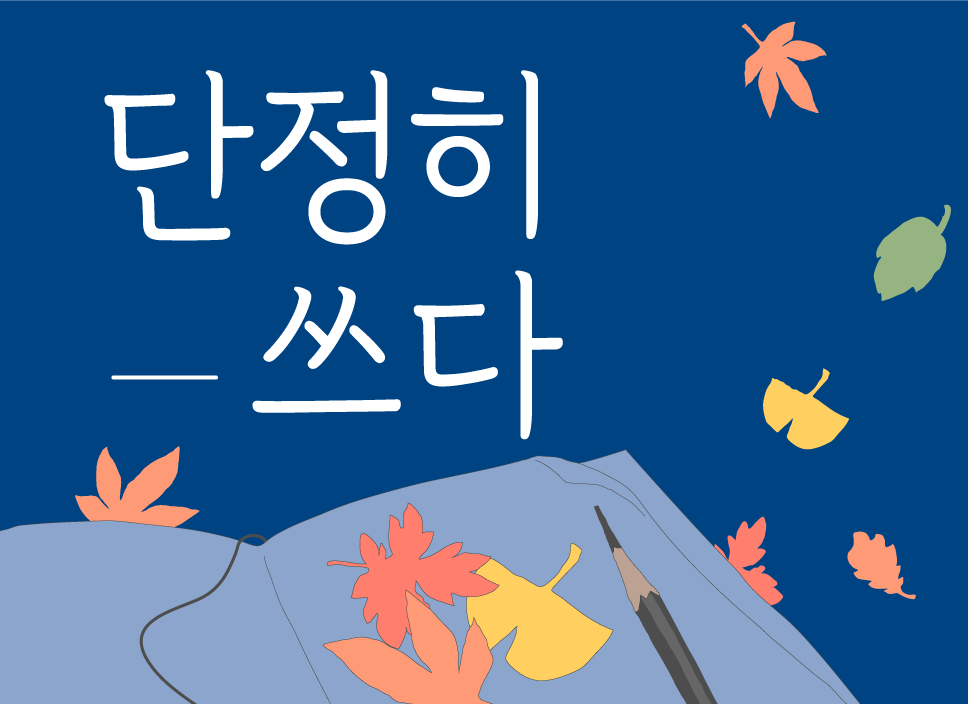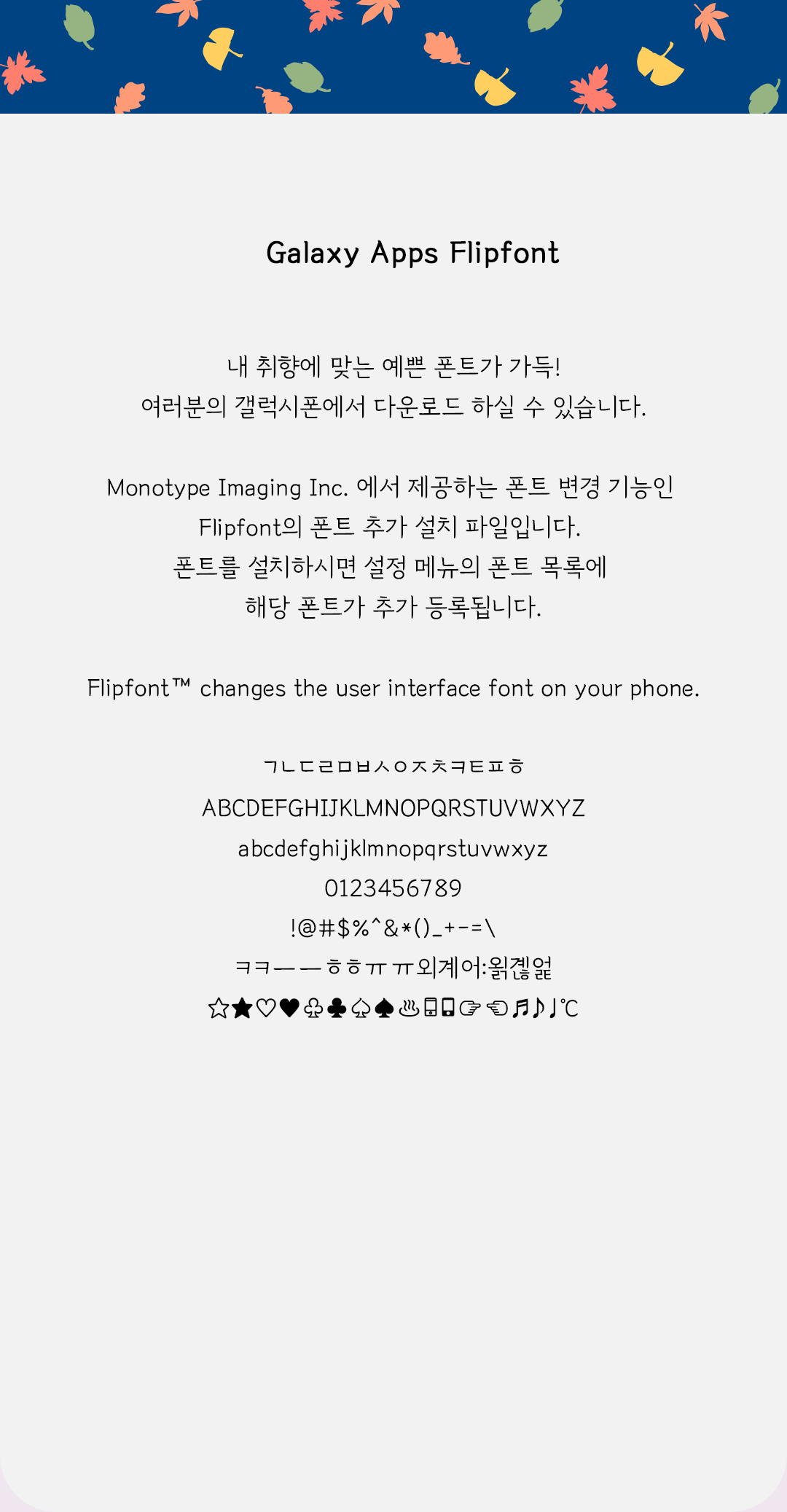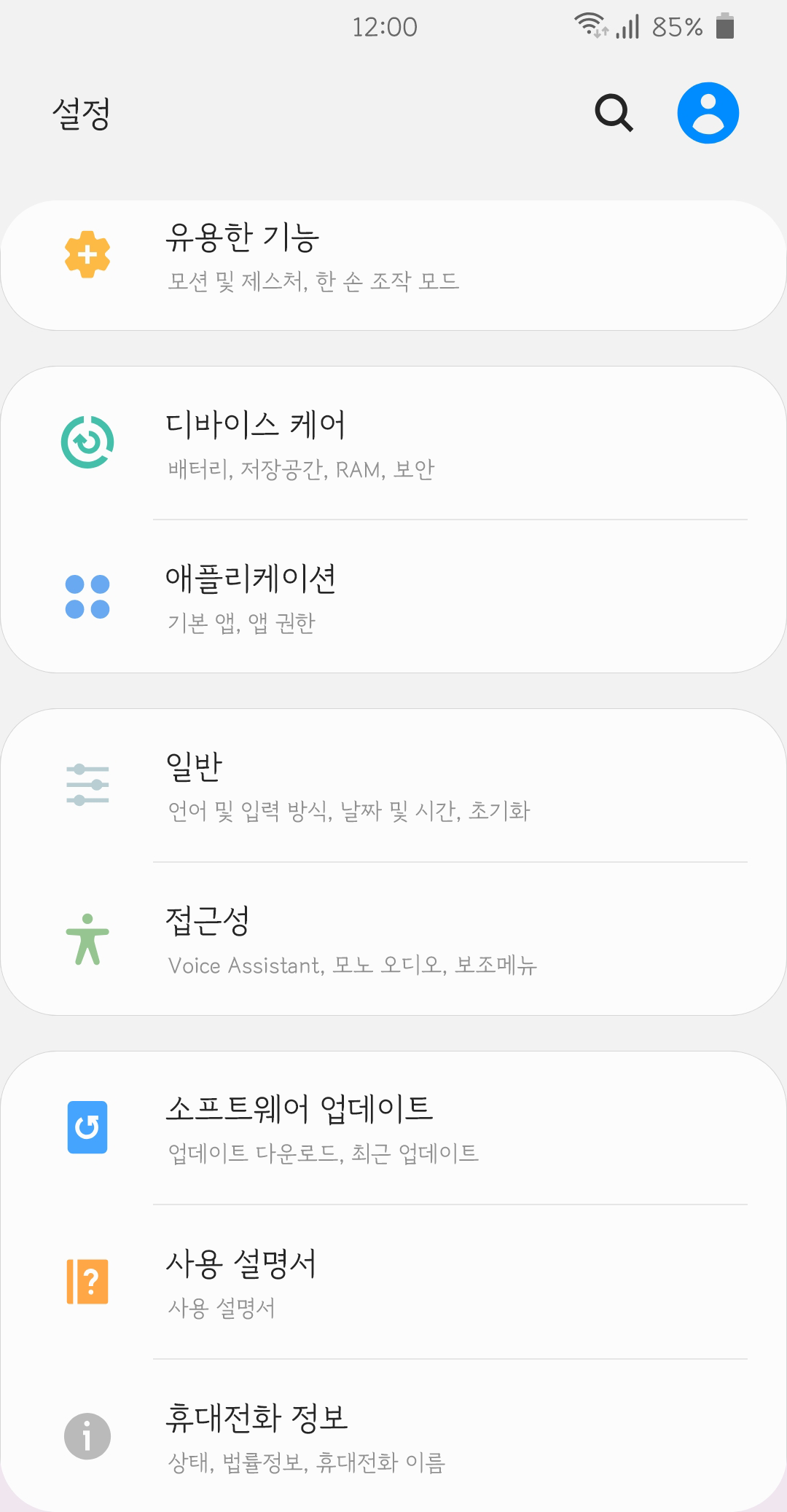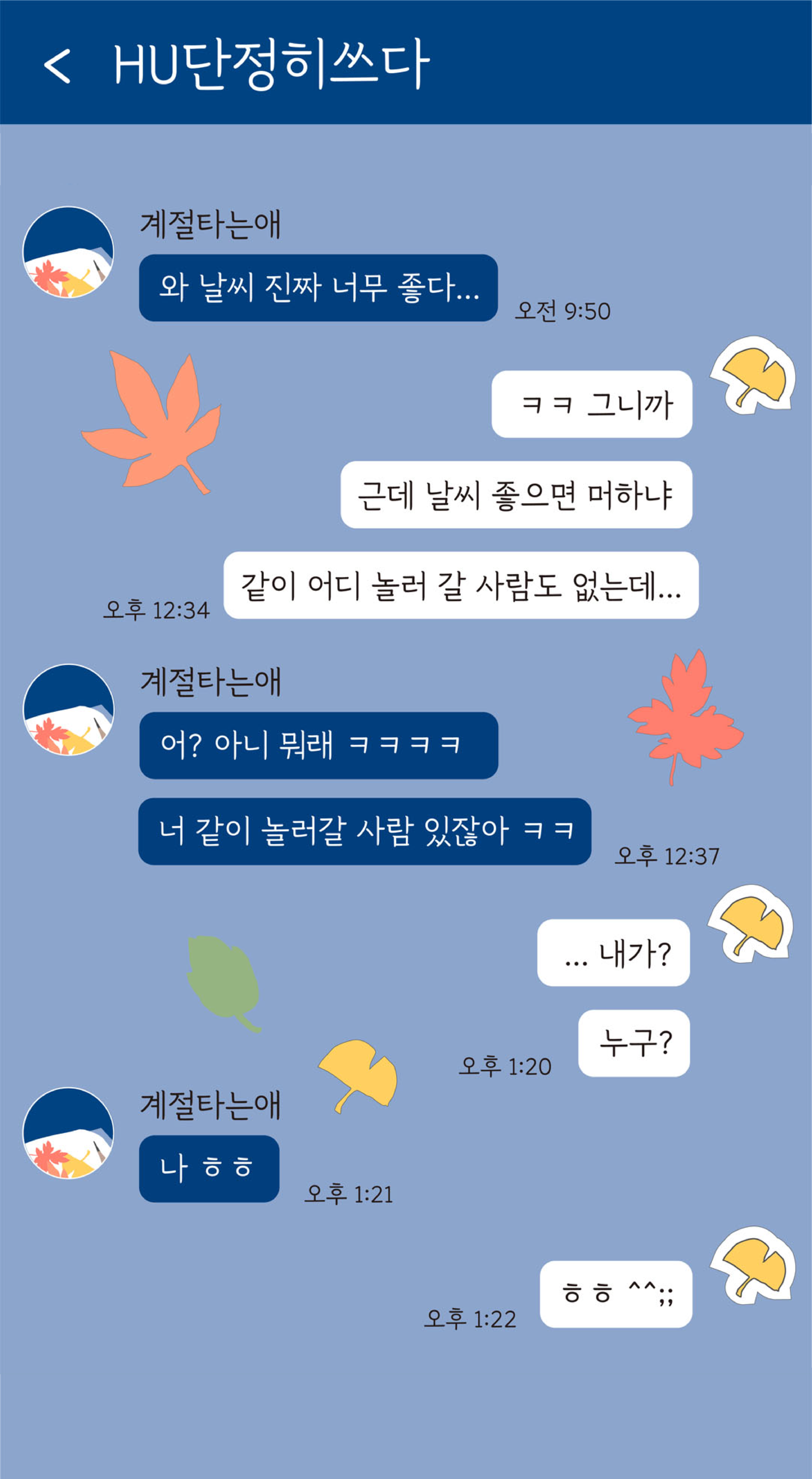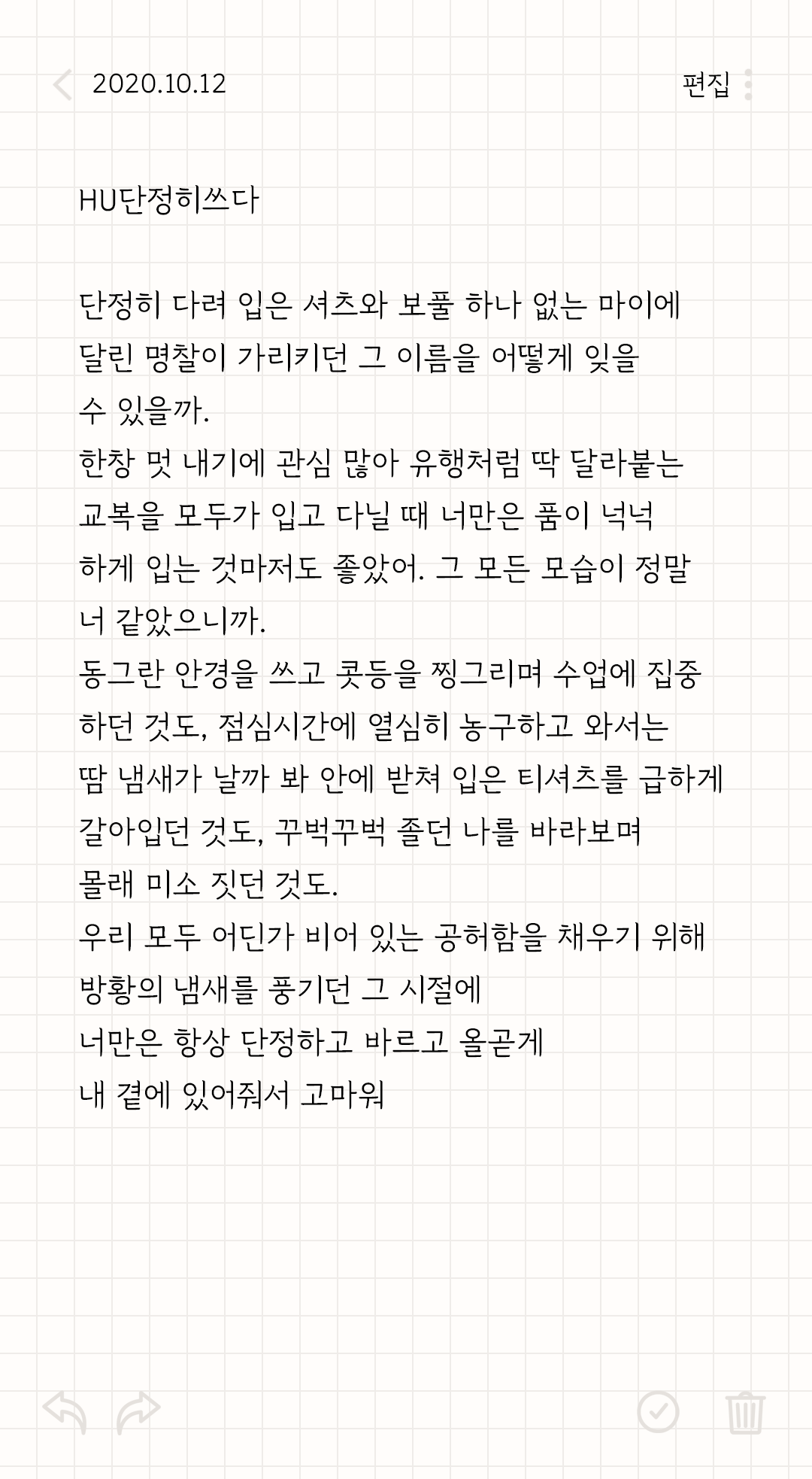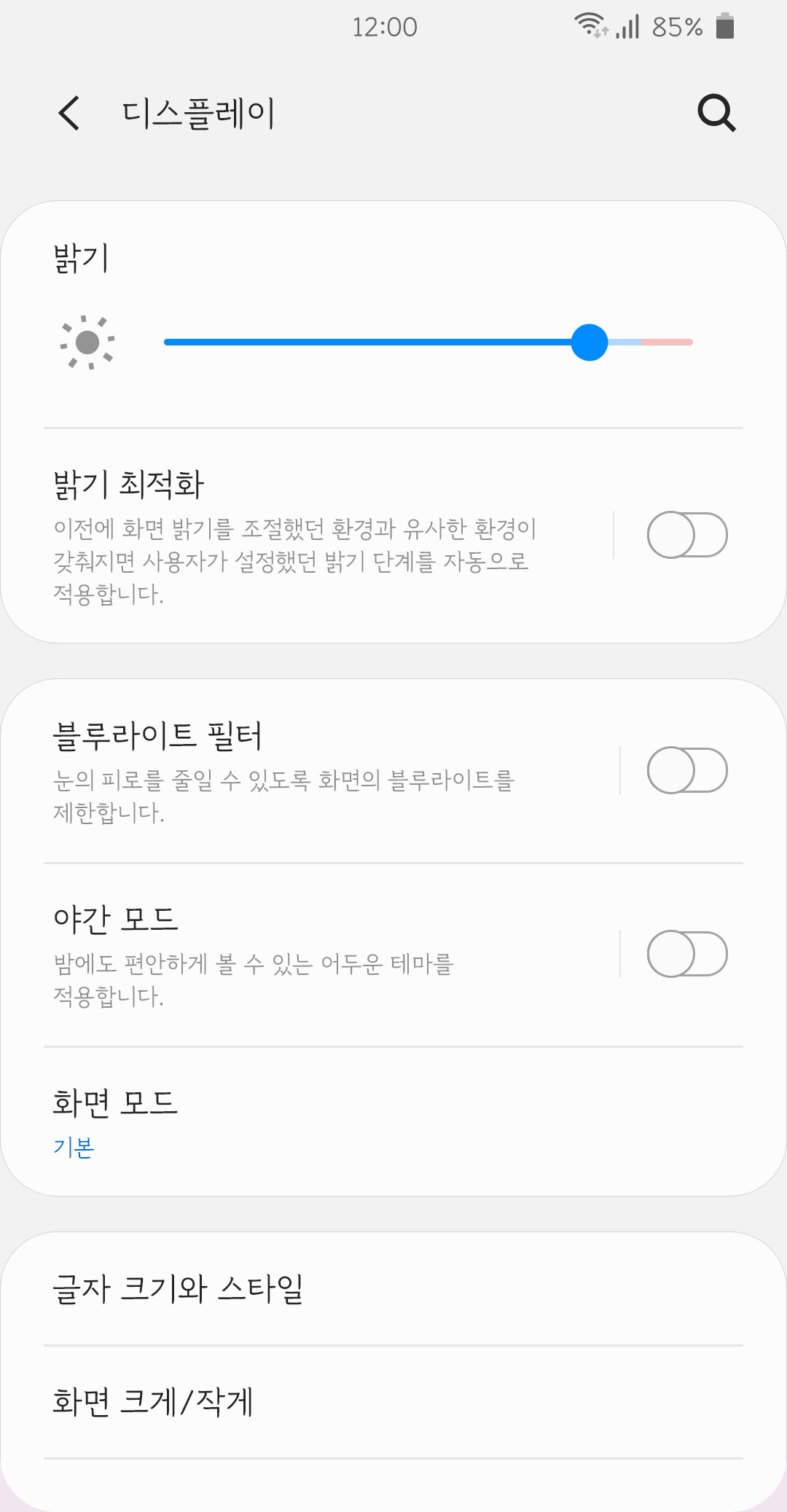
단정하게 손으로 직접 쓴 듯한 자연스러운 획과 담백한 세리프 형태를 가진 서체입니다.
명조 느낌의 세리프로 눈의 피로도는 줄이고 가독성을 높였습니다.
'ㅅ','ㅈ','ㅊ' 세 자음의 가운데에 공간을 두어 개성있고 단정한 손글씨 느낌을 더한 서체입니다.
단정하게 손으로 직접 쓴 듯한 자연스러운 획과 담백한 세리프 형태를 가진 서체입니다.
명조 느낌의 세리프로 눈의 피로도는 줄이고 가독성을 높였습니다.
'ㅅ','ㅈ','ㅊ' 세 자음의 가운데에 공간을 두어 개성있고 단정한 손글씨 느낌을 더한 서체입니다.